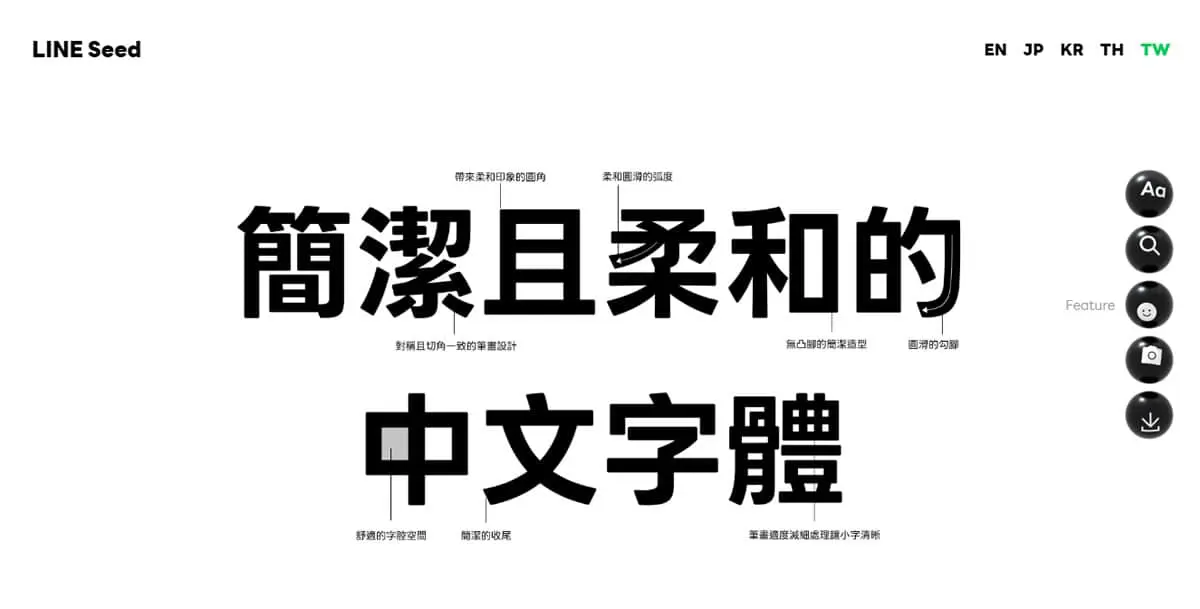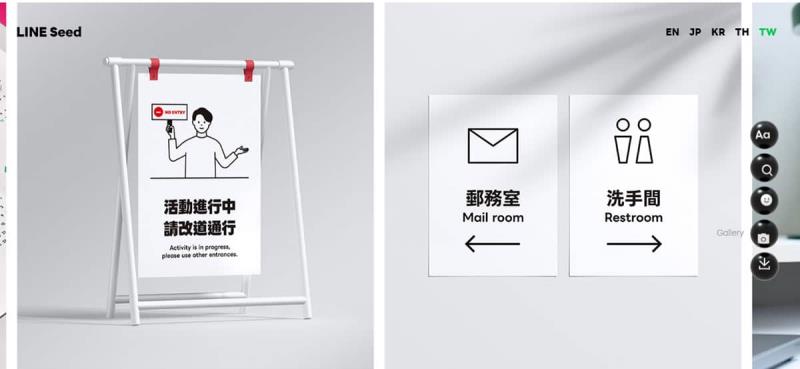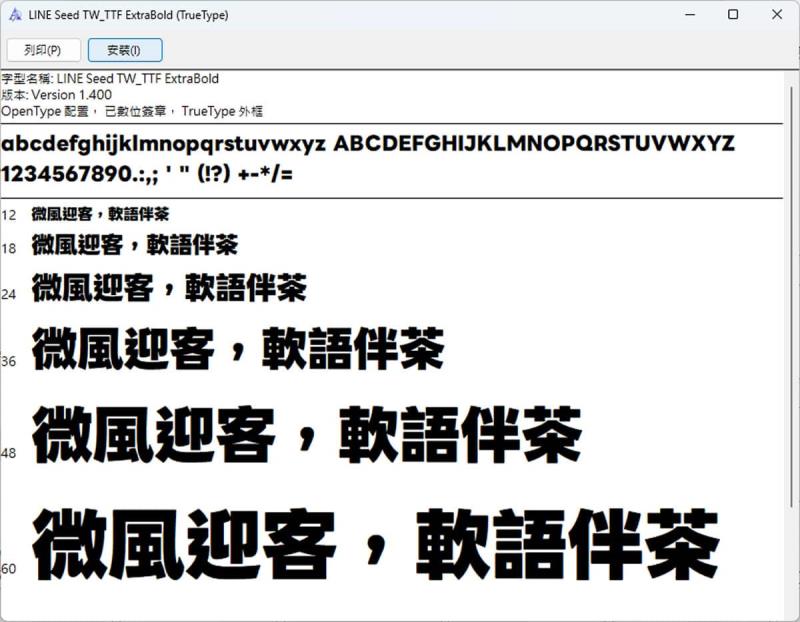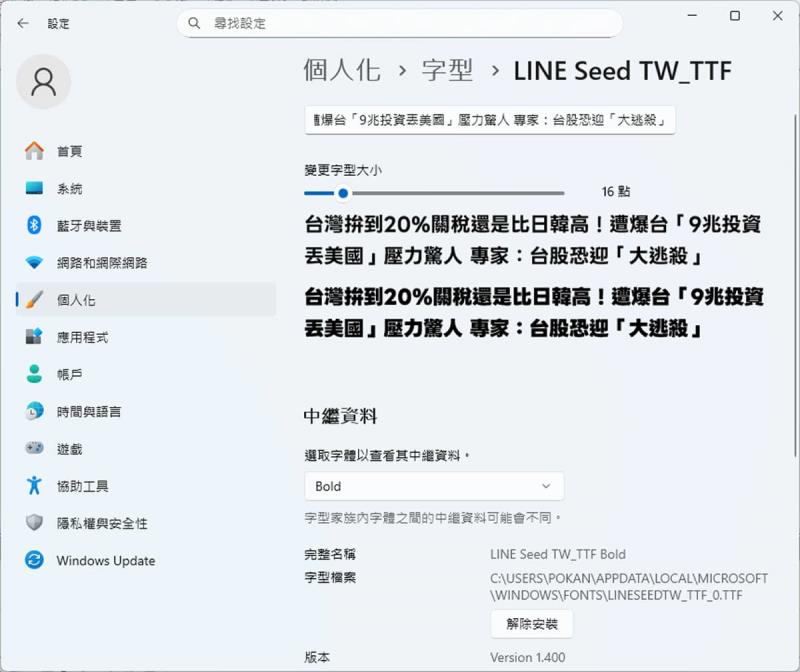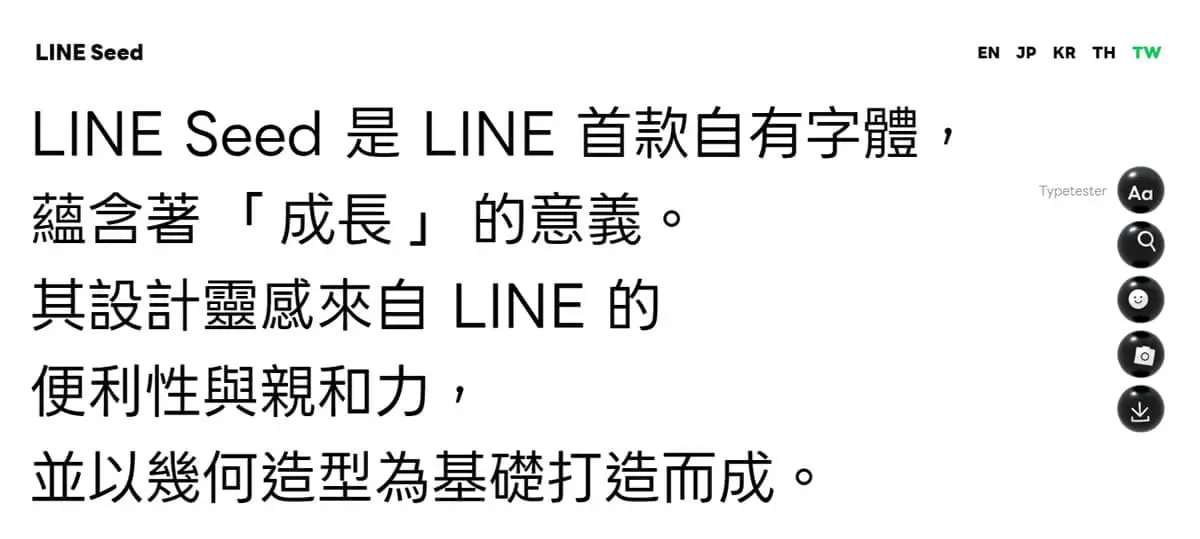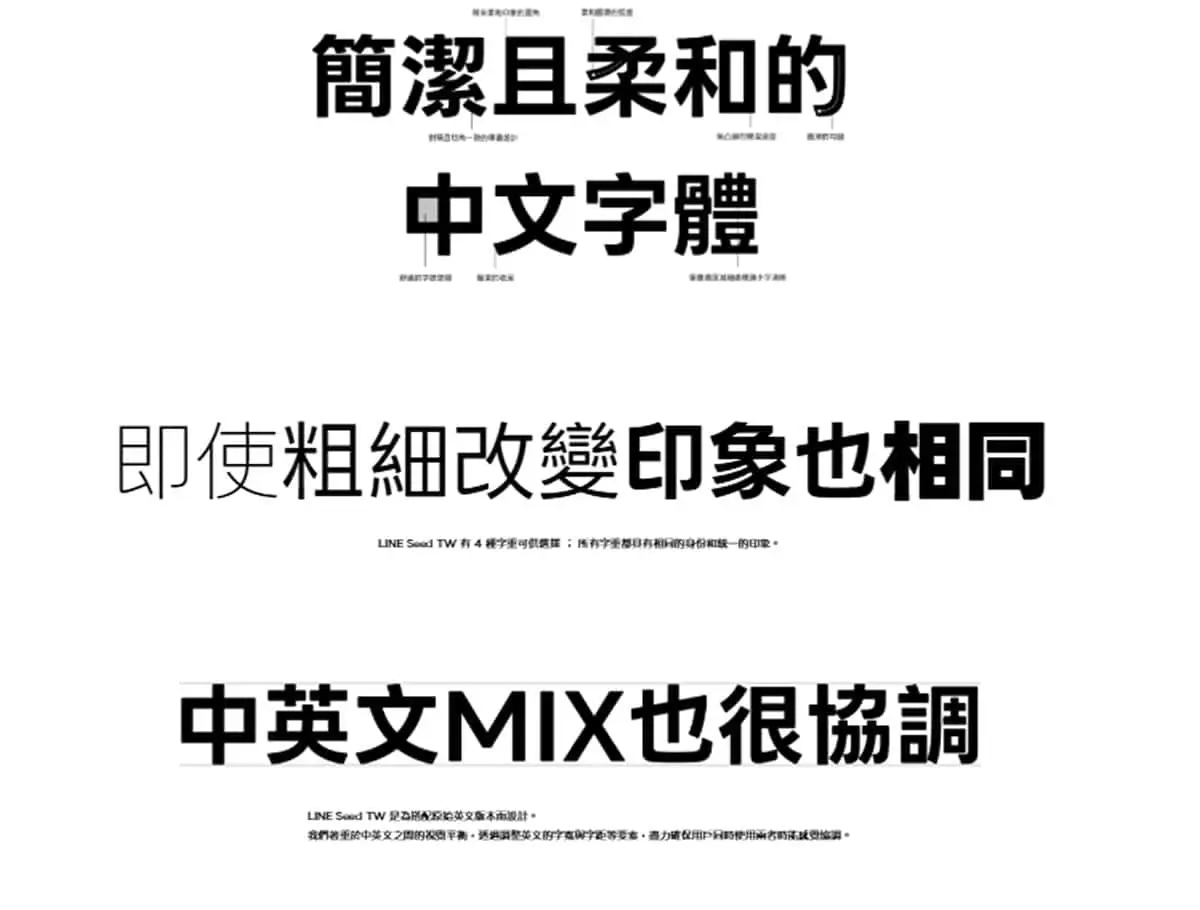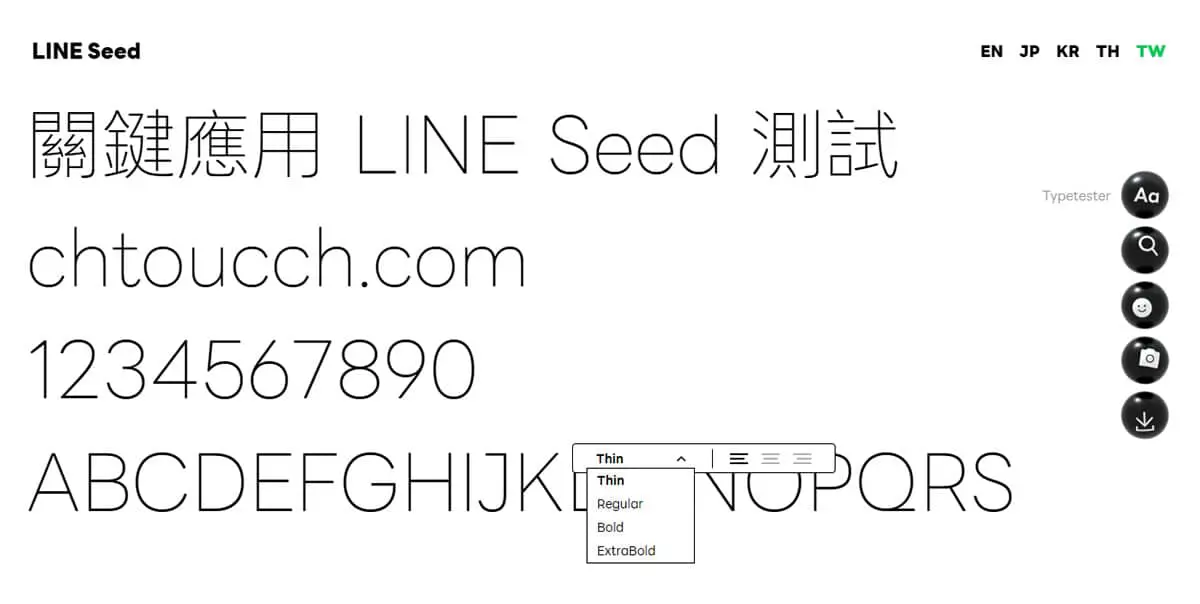
LINE 正式推出自家開發的企業字型「LINE Seed TW」,這是一套專為繁體中文使用者設計的免費字型。LINE Seed 是基於 LINE 的便利性與親和力打造的新字體,象徵著種子發芽並結成果實的概念,寓意著字型深植於 LINE 服務中,與使用者一同成長茁壯。
這套字型並非憑空而生,而是在日文、英文、韓文、泰文版本推出後,特別針對繁體中文市場打造的完整版本。現在終於補齊繁中支援,讓使用者在多語言環境下也能保持視覺一致性。
圓角設計融入漢字,打造親和力十足的視覺體驗
LINE Seed TW 最大的特色就是將 LINE 品牌標誌性的圓角設計融入字型設計中。LINE 商標獨特的圓角設計被應用於所有文本元素,包括文字、數字、符號與圖標,確保整體風格的一致性與品牌識別度。這種圓潤風格讓整體文字看起來更加溫和親切,符合 LINE 一貫的親民形象。不管是在數位螢幕上閱讀,還是印刷品上使用,都能呈現出舒適的視覺效果。
華康字型與 LINE 聯手打造,專業品質保證
LINE Seed TW 是由華康字型(威鋒數位)和 LINE 攜手打造,融合雙方專業與品牌精神,精心設計而成。華康字型在中文字型設計領域擁有豐富經驗,這次的企業字體合作可說是相當珍貴的組合。透過這次合作,不僅展現了字型設計的專業技術,也體現了 LINE 對於品牌視覺一致性的重視。
2.LINE Seed TW 有 4 種字重可供選擇,所有字重都具有相同的身份和統一的印象。
- Thin(極細體):適合用於高級感設計、時尚品牌應用、或是需要營造輕盈氛圍的場合。常見於雜誌內頁的輔助文字、產品型錄的規格說明、或是網站中的次要資訊標示。但要注意在小尺寸或低解析度螢幕上可能會有可讀性問題。
- Regular(標準體):這是最常使用的字重,適合大部分的內文排版需求。不管是文章內容、說明文字、介面文字、或是一般的印刷品內文,Regular 都能提供良好的閱讀體驗。它在各種尺寸下都有不錯的清晰度,是最安全也最實用的選擇。
- Bold(粗體):主要用於強調重點資訊,像是標題、重要提醒、按鈕文字、或是需要突出的關鍵字。在網頁設計中常用於導航選單、CTA 按鈕(Call To Action,行動呼籲)、或是文章的小標題。Bold 字重能有效吸引注意力,但不宜大面積使用。
- ExtraBold(特粗體):適合用於大標題、海報主標、廣告標語、或是品牌 Logo 等需要強烈視覺衝擊的場合。這個字重非常搶眼,通常用於短文字的展示,像是促銷活動標題、重要公告、或是需要遠距離觀看的指示牌文字。